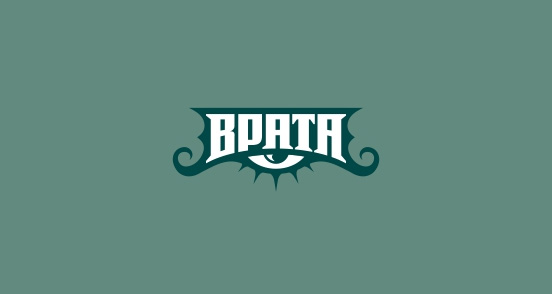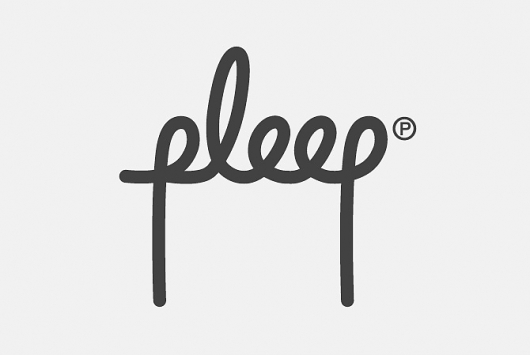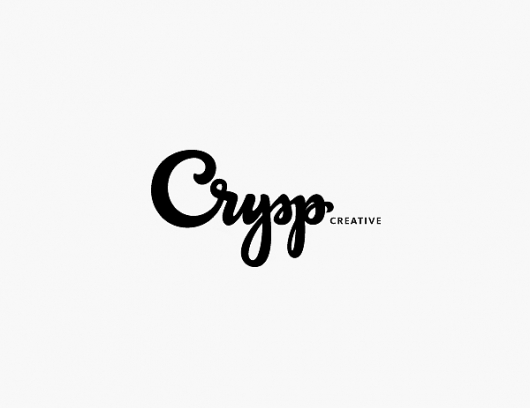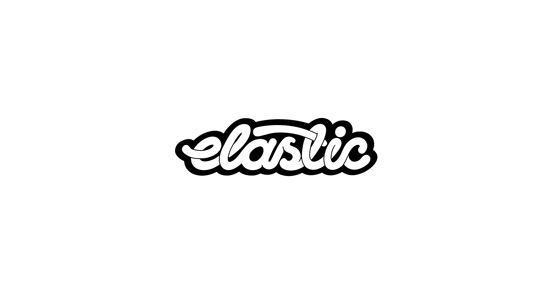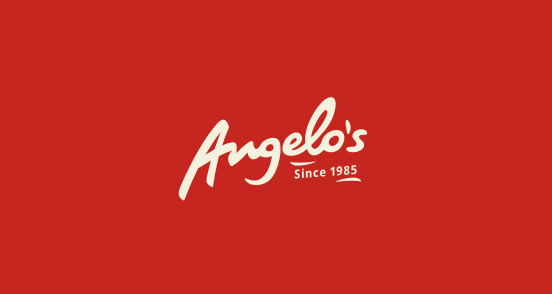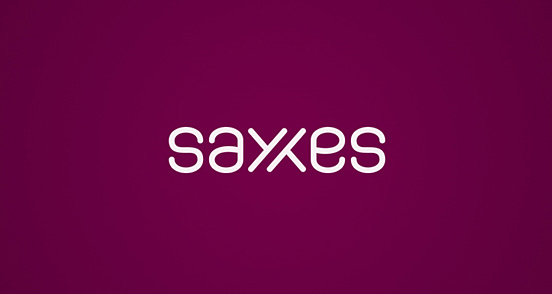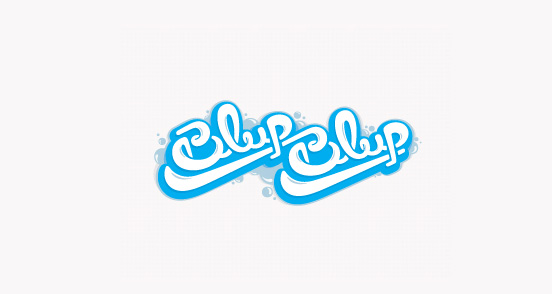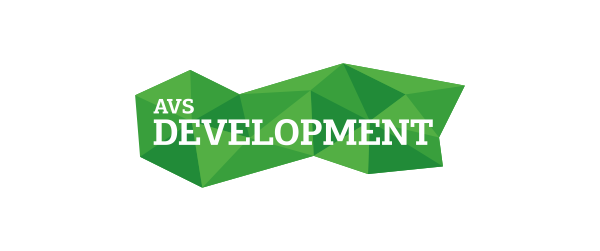
Ya en posts anteriores hemos mencionado la importancia de las tipografías en diseños de logos y los resultados que podríamos lograr haciendo un buen uso de ellas, en este post les compartimos una recopilación de 50 diseños de logos tipográficos o mejor dichos ejemplos de logos que utilizan tipografías como elemento principal.
Algo que se debe destacar en estos diseños es como sus autores jugaron con las formas tipográficas para lograr diseños originales y únicos que llaman la atención y lograr comunicar una idea, en fin les dejo algunos de los diseños y en la liga final podrán ver todos los diseños de logos para inspirarse.